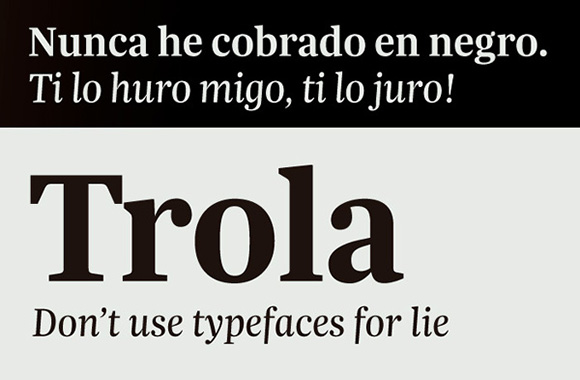
Jordi Embodas empieza a ser un viejo conocido por aquí, pero es que últimamente no hace más que regalarnos una joya tipográfica tras otra. Su nueva creación se llama Trola y llega para complementar a la «sin serifa» Bulo, con la que comparte esqueleto formando un duo sencillamente genial.
Al estar pensada para prensa, es característica indispensable el ahorro de espacio, por lo que es ligeramente condensada en horizontal, posee unas ascendentes y descendentes cortas y tiene un gran ojo medio. Jordi ha tenido en cuenta estos aspectos para la prensa en papel y su obsesión por meter cuantos más caracteres en una página, pero no se ha olvidado de los medios digitales y por ello Trola tiene un contraste moderado para manchar mejor en pantalla. Caben destacar también sus dos pesos para texto (Regular y Light) y los tres para titulares (Semibold, Bold y Heavy) de tal manera que es muy fácil matizar entre estilos.